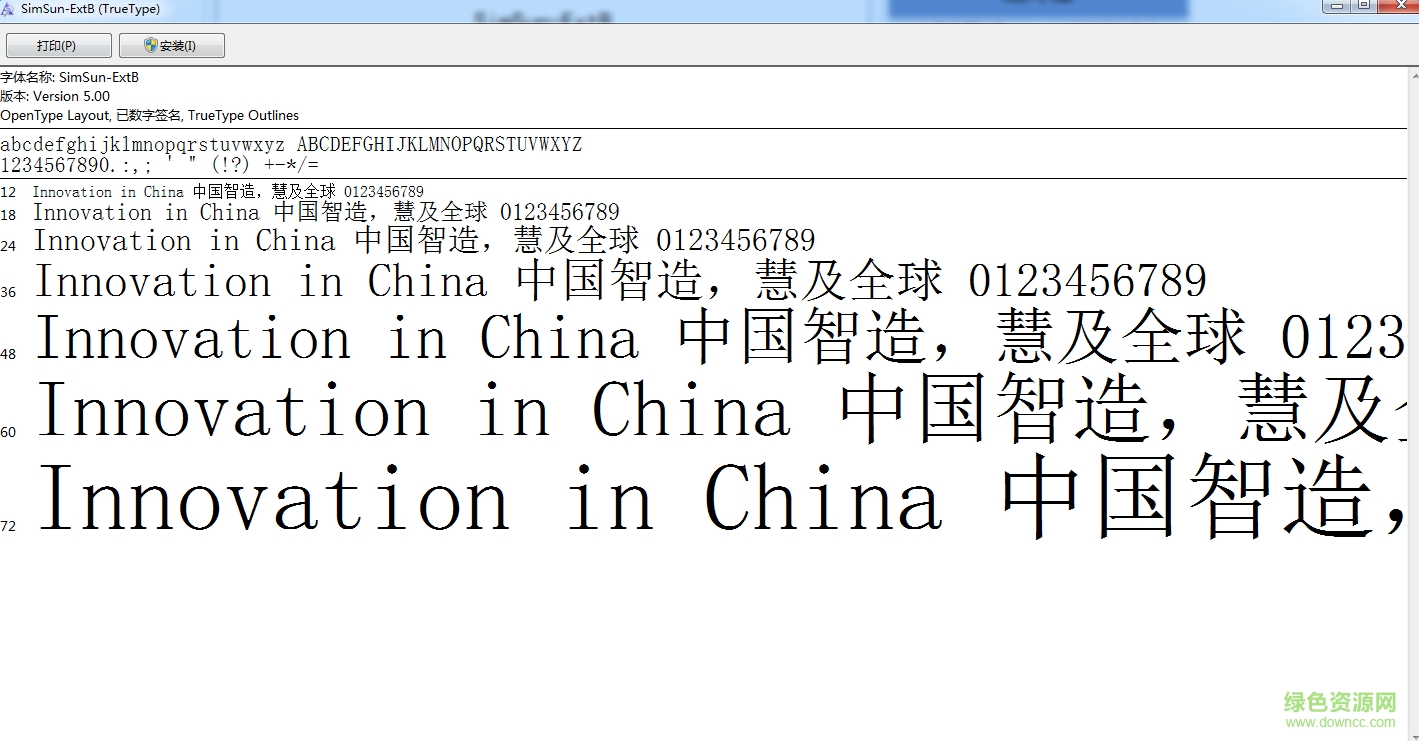
simsunextb是什么字體?simsun extb字體其實就是包括擴展字符(B)的宋體字的英文名稱,該字體粗細變化得宜,字形標(biāo)準(zhǔn),應(yīng)用廣泛,需要該字體的小伙伴歡迎在綠色資源網(wǎng)下載~!
宋體,是為適應(yīng)印刷術(shù)而出現(xiàn)的一種漢字字體。筆畫有粗細變化,而且一般是橫細豎粗,末端有裝飾部分(即「字腳」或「襯線」),點、撇、捺、鉤等筆畫有尖端,屬于襯線字體(serif),常用于書籍、雜志、報紙印刷的正文排版。宋體是生而具來的印刷體,產(chǎn)生于雕版,成型于明朝。
現(xiàn)代鉛字采用了宋體印刷。后來依據(jù)西方文字的黑體和意大利體的方式,在漢字印刷體中也創(chuàng)造了黑體的鉛字。目前宋體、黑體、仿宋體和楷體成為漢字印刷的主要四種字體?!杆误w」是一類字體的總稱,有很多字體都屬于這個范疇。